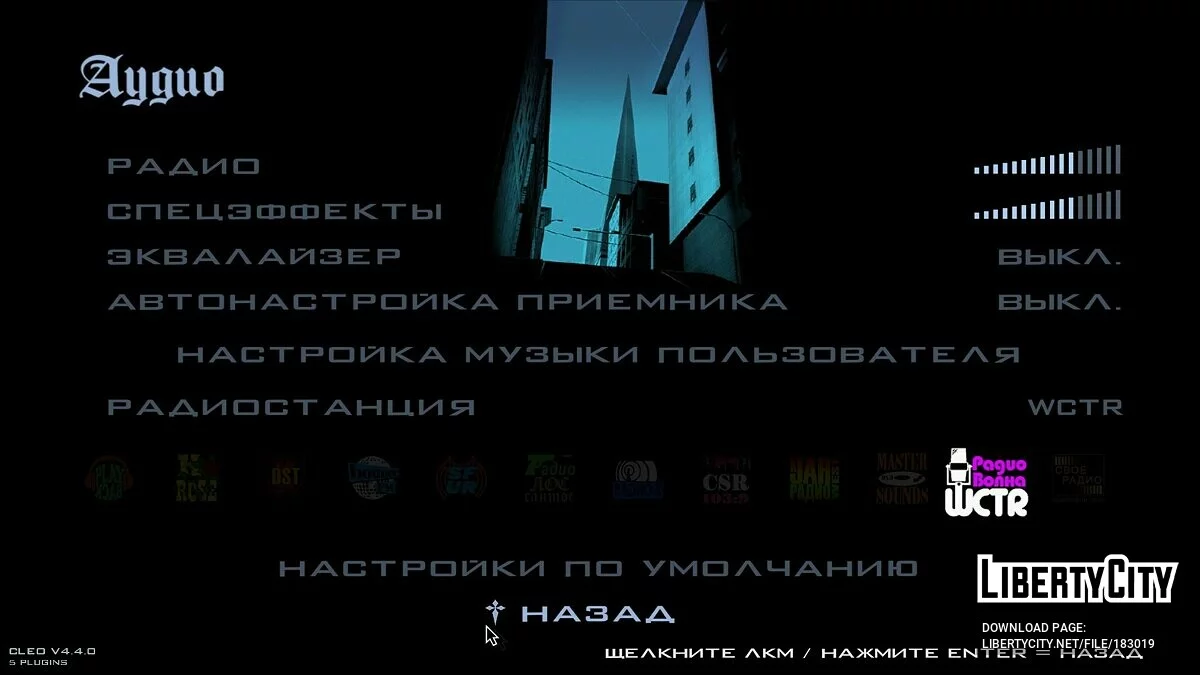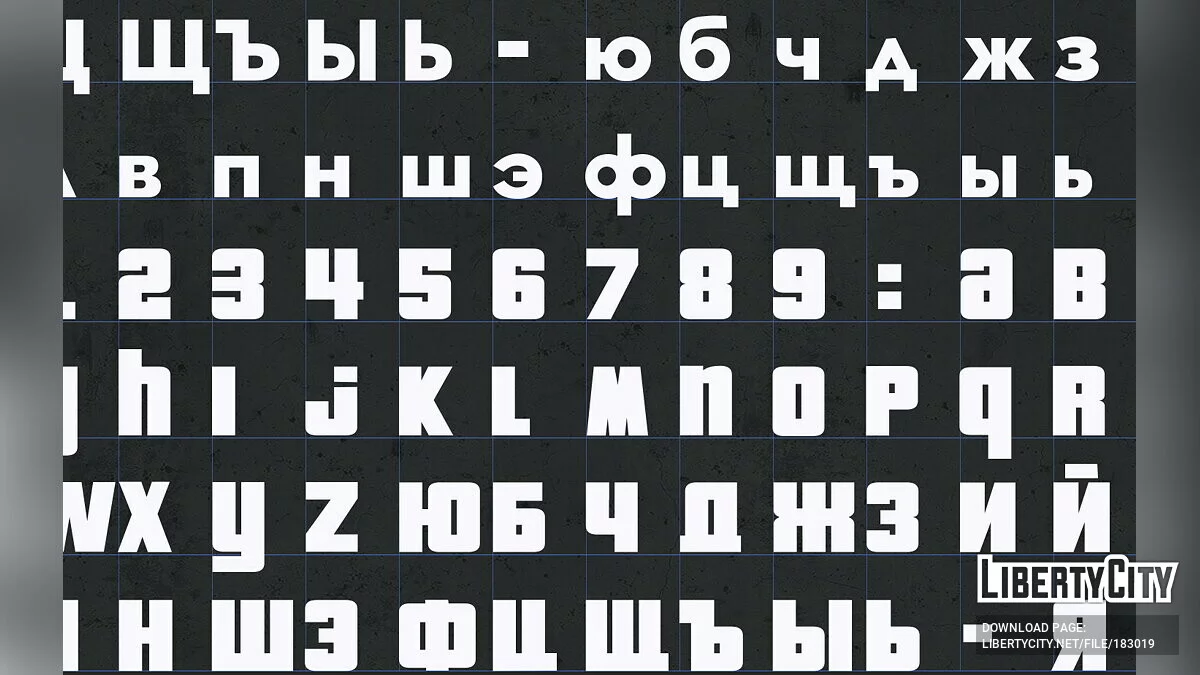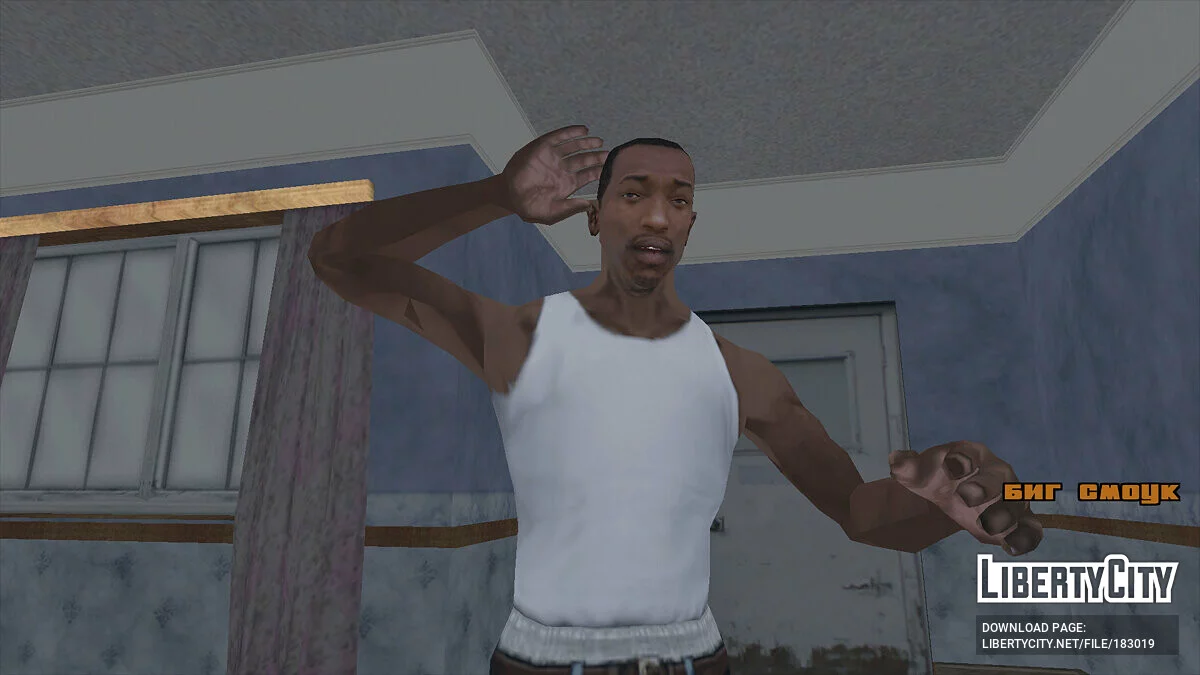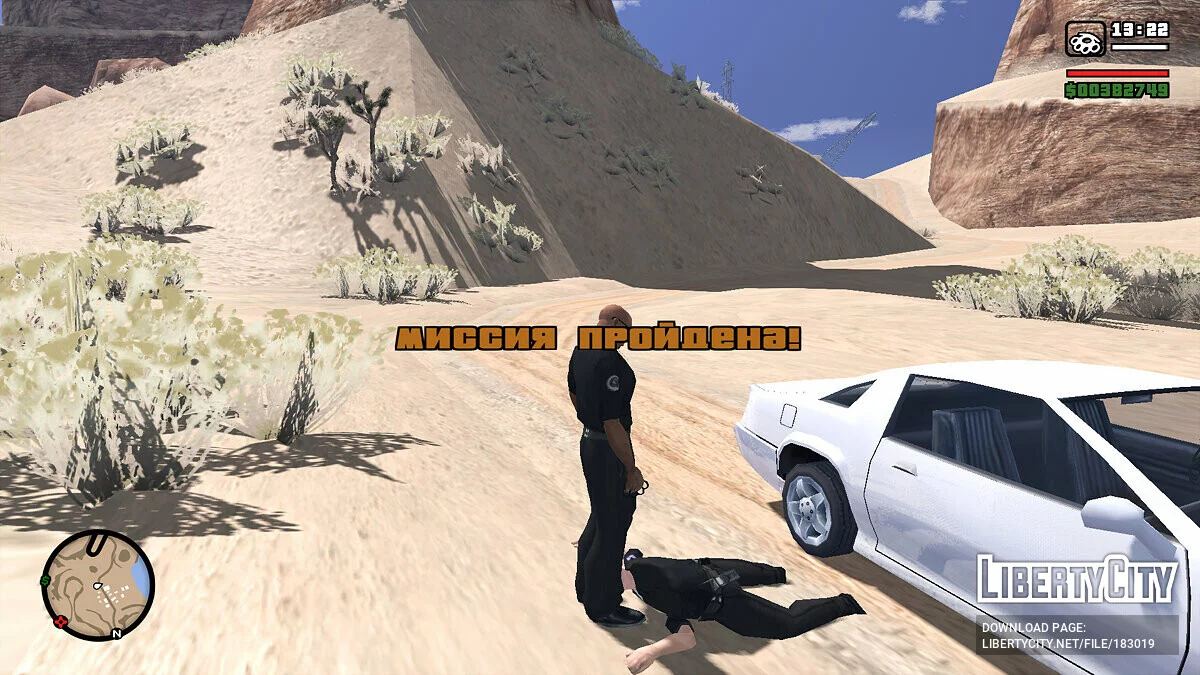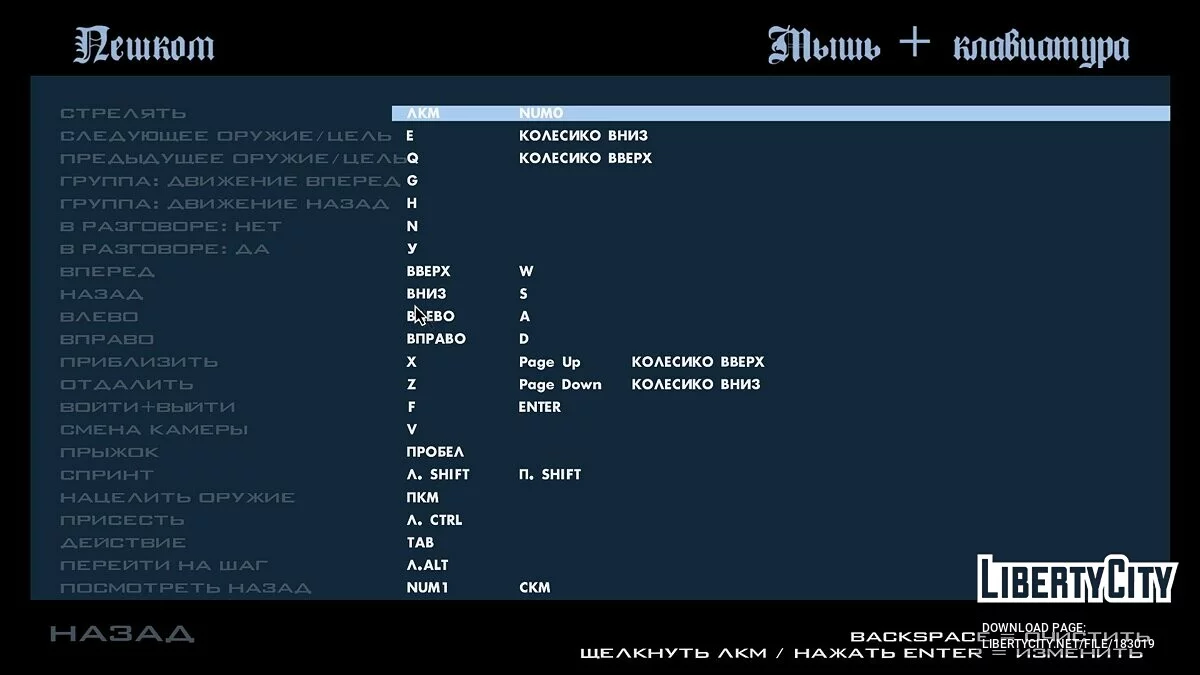
HD-шрифты для русификатора 1С (v. 1.01)
Формат шрифтовых карт 1024х1024рх.
Немного расставил символы, провел цветокоррекцию, некоторые символы постарался сделать, как в оригинале.
В версии 1.01
Исправлено:
положение символа \"M\" (жирный квадратный шрифт) и ширина поля данного символа при печати.